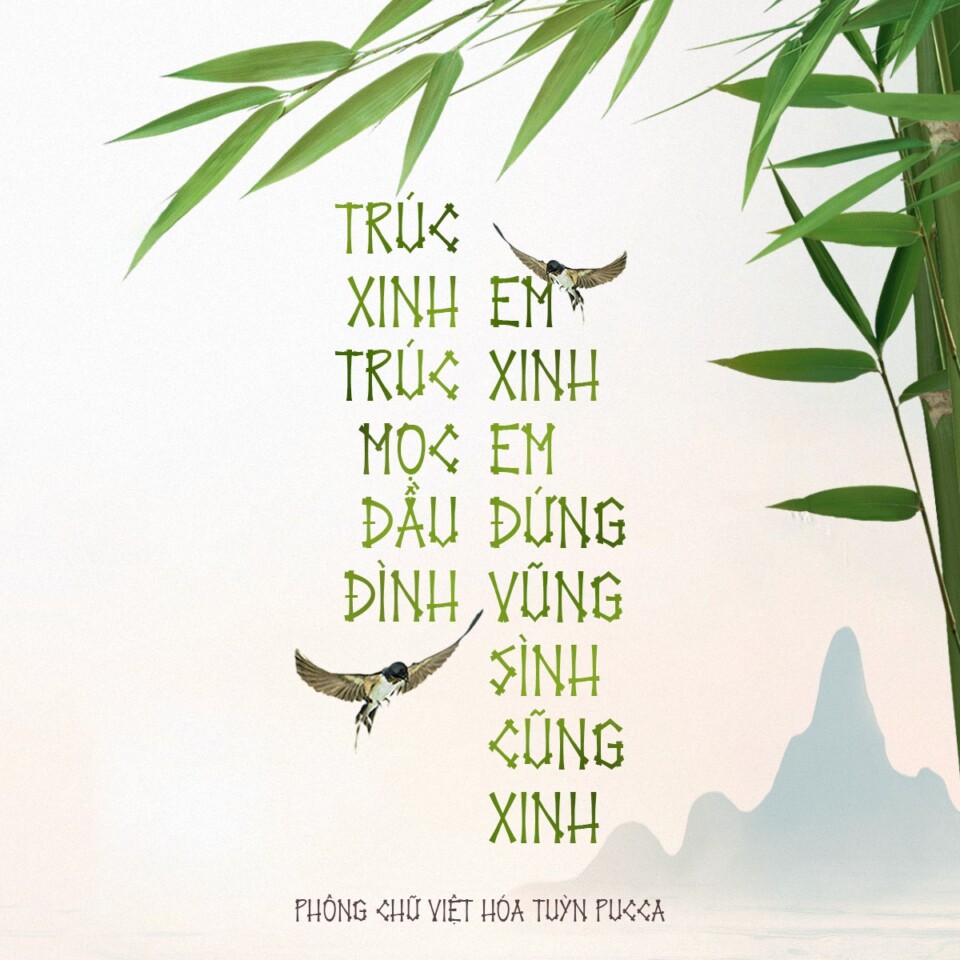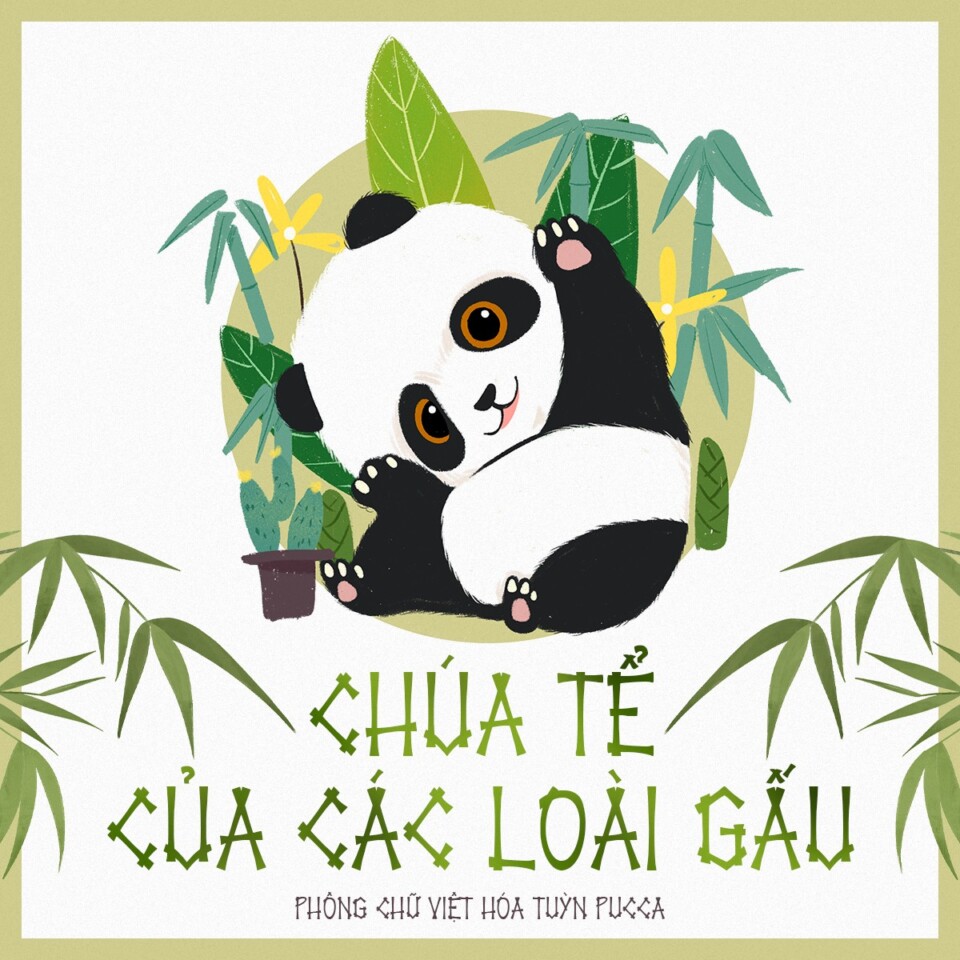
Trong thế giới thiết kế ngày càng đa dạng và sáng tạo, việc lựa chọn font chữ phù hợp không chỉ giúp truyền tải thông điệp hiệu quả mà còn góp phần thể hiện bản sắc văn hóa riêng biệt. Một trong những font chữ mang đậm dấu ấn Á Đông và thiên nhiên chính là font Bamboo.
Đặc điểm nổi bật của font Bamboo
Lấy cảm hứng từ thiên nhiên
Font Bamboo được thiết kế mô phỏng theo hình dáng của cây tre – một biểu tượng quen thuộc trong văn hóa Á Đông. Các đường nét của chữ thường thanh mảnh, thẳng đứng, có điểm gãy giống như các đốt tre tự nhiên, tạo cảm giác mộc mạc và gần gũi.
Phong cách thư pháp – nghệ thuật
Font này thường kết hợp giữa yếu tố hình học và nét bút viết tay, tạo nên sự hòa quyện giữa tính hình thức và cảm xúc. Điều đó mang lại nét mềm mại và nghệ thuật trong từng ký tự, rất phù hợp với các thiết kế mang tính biểu cảm cao.
Việt hóa và dễ sử dụng
Một số phiên bản font Bamboo đã được Việt hóa, hỗ trợ đầy đủ bảng chữ cái tiếng Việt có dấu, giúp người dùng dễ dàng áp dụng trong các thiết kế nội dung, in ấn mà không gặp lỗi hiển thị.
Phong cách Á Đông đậm nét
Font Bamboo mang hơi hướng văn hóa phương Đông – đặc biệt là Việt Nam, Trung Quốc, Nhật Bản – nên khi sử dụng trong thiết kế sẽ dễ gợi cảm giác truyền thống, thiền định, tự nhiên và tinh tế.
Ứng dụng của font Bamboo
Ấn phẩm truyền thống
Font Bamboo rất phù hợp cho các poster, banner, bao bì sản phẩm, tem nhãn mang chủ đề về thiên nhiên, thảo mộc, nông sản, thủ công mỹ nghệ… Đặc biệt thích hợp cho thương hiệu thiên nhiên, organic hoặc các sản phẩm địa phương.
Thiết kế nhà hàng, quán ăn, tiệm trà, spa phong cách Á Đông
Nhờ vào hình ảnh đặc trưng gắn với tre, trúc, font Bamboo tạo nên dấu ấn văn hóa rất riêng. Đây là lựa chọn hoàn hảo khi bạn muốn thiết kế bảng hiệu, menu, bao bì cho nhà hàng, quán ăn chay, spa theo phong cách thiền, nhẹ nhàng và thanh tịnh.
Trang trí sự kiện, poster lễ hội, ấn phẩm truyền thống
Các sự kiện như Tết, lễ hội văn hóa, các buổi trình diễn nghệ thuật truyền thống cũng có thể sử dụng font Bamboo để tăng thêm tính bản sắc, cổ truyền nhưng vẫn giữ được nét thẩm mỹ hiện đại.
Font Bamboo là sự kết hợp độc đáo giữa thiên nhiên và nghệ thuật chữ viết, thể hiện nét đẹp mộc mạc nhưng tinh tế. Nếu bạn đang cần một font mang đậm dấu ấn văn hóa Á Đông, dễ ứng dụng trong các thiết kế về thiên nhiên, truyền thống hay thư giãn – thì Bamboo là lựa chọn đáng cân nhắc.